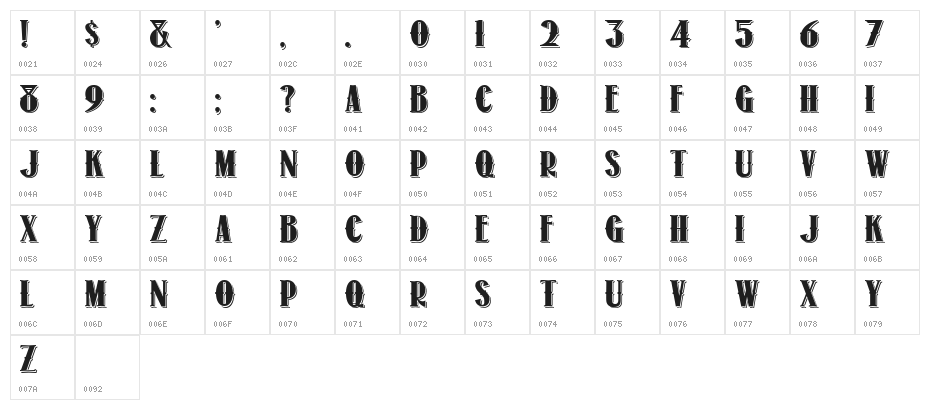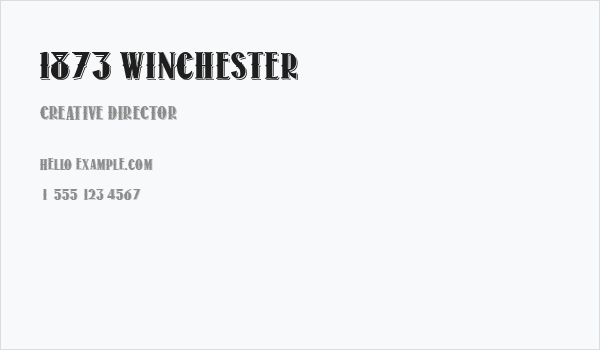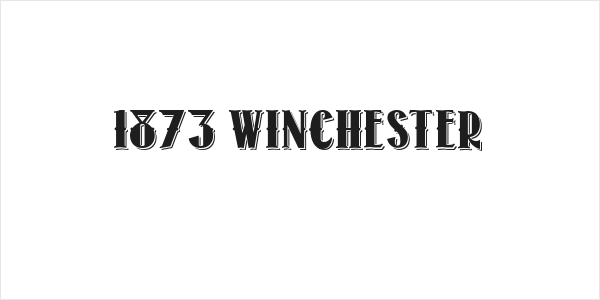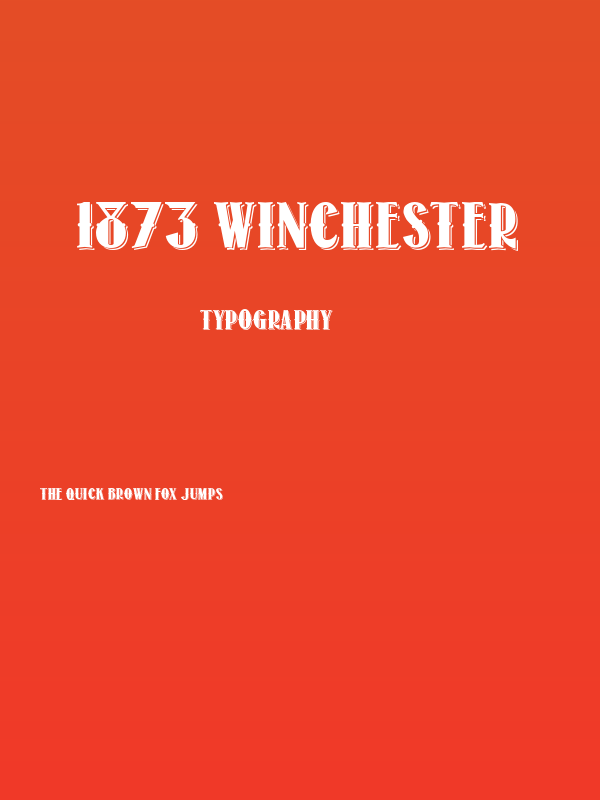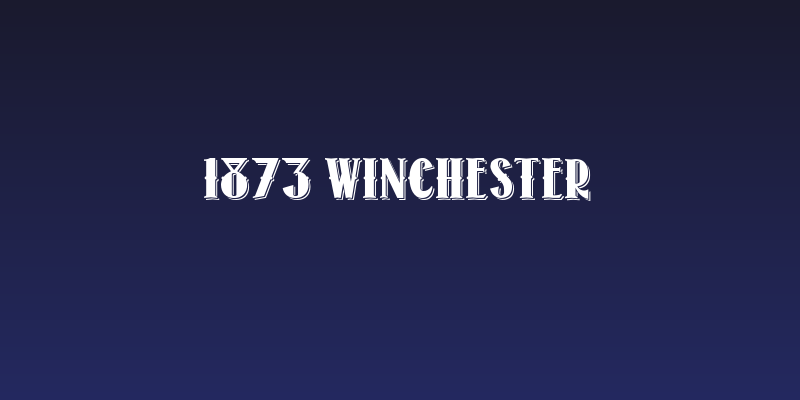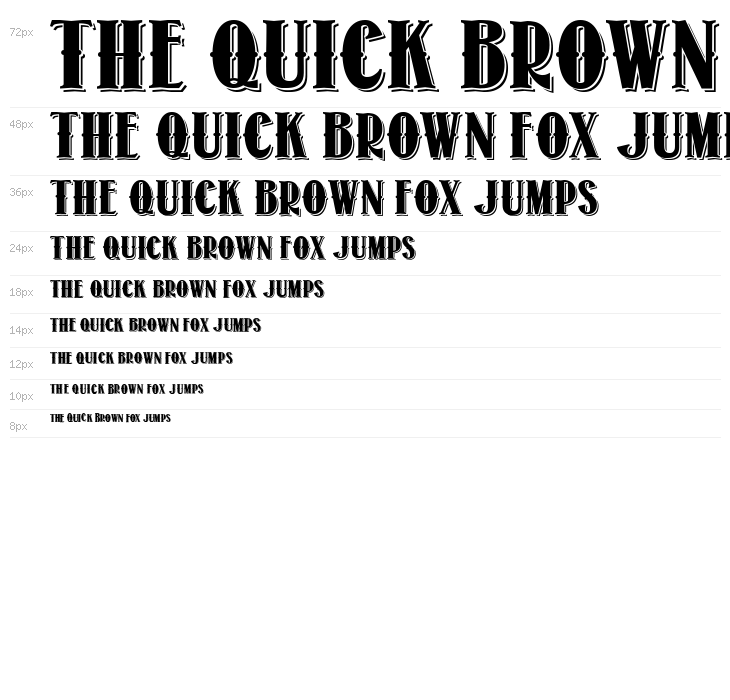
1873 Winchester Font
| Progetti proposti | Ideal for Western-themed posters, vintage signage, branding for rustic or historical events, and any design requiring a bold, eye-catching typeface. |